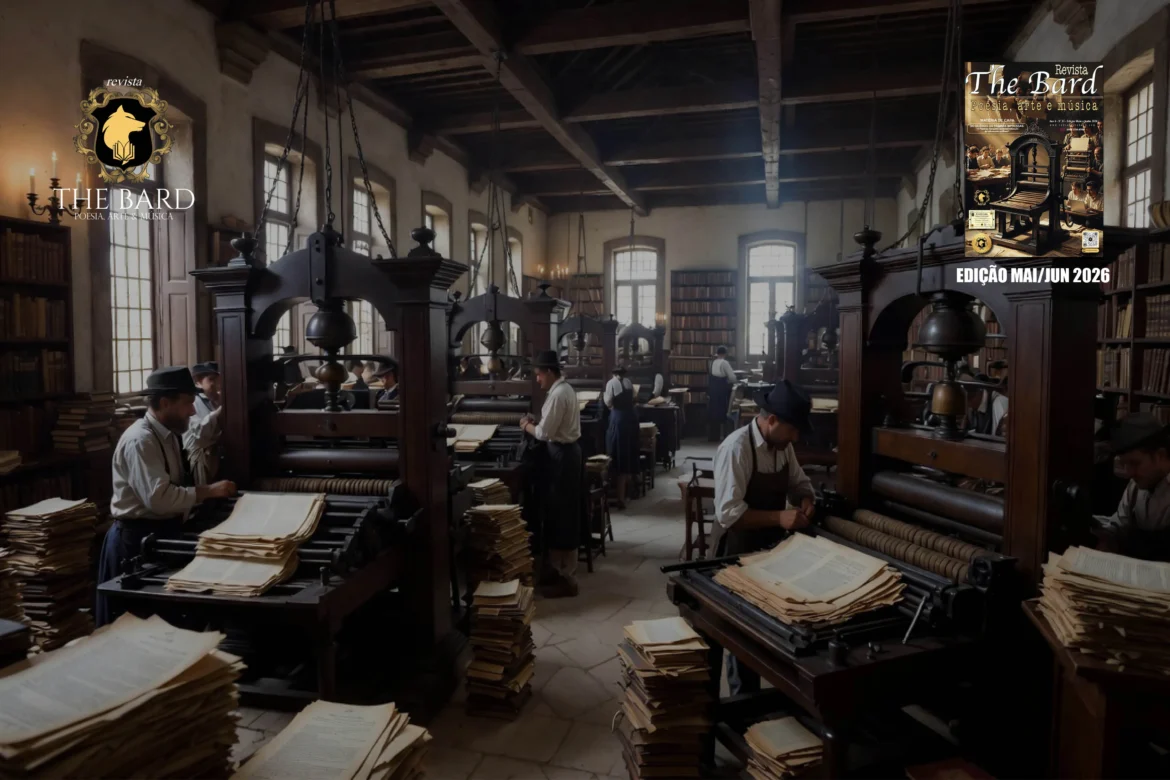
“A tipografia é o ofício que dá forma visível e durável –
e portanto existência independente – à linguagem humana.”
Robert Bringhurst
A junção das letras deu origem a escrita, há cerca de 4000 a.C., permitiu que a humanidade registrasse seus modos de vida, atravessando barreiras do tempo e preservando informações para o futuro. No mundo antigo, especialmente nas civilizações do Oriente Próximo, como o Egito e a Mesopotâmia, a escrita era um instrumento de poder e controle, raramente acessível à população comum (camponeses, artesãos). Na maior parte da antiguidade a escrever era uma habilidade especializada, restrita e dominada majoritariamente por escribas e sacerdote. Dominar a escrita trazia reconhecimento social e isenção de trabalhos braçais, posicionando os escribas como um grupo de elite, embora abaixo da nobreza e dos altos sacerdotes.
As letras viram palavras, que viram frases,
que viram histórias, que tocam os corações.
Autor desconhecido
Surgimento da tipografia
A escrita era feita à mão por escribas, o que tornava os livros raros e caros. Diferente dessa produção manual a tipografia é a arte, técnica e processo de organizar letras, fontes e caracteres para tornar a linguagem escrita legível, clara e visualmente atraente. Práticas de impressão em superfícies macias já existiam na Mesopotâmia (selos) e China (blocos de madeira no século II d.C.), contudo, o surgimento da tipografia moderna é marcado pela invenção da prensa de tipos móveis metálicos por Johannes Gutenberg na Alemanha, por volta de 1450, criando letras e símbolos em relevo esculpidos em metal, capazes de aumentar os números na produção, diminuir o valor em cima, e disseminar a informação. O primeiro livro inteiro publicado pela técnica da imprensa foi a bíblia.
História da tipografia no Brasil
No Brasil, a história da tipografia se mistura às transformações sociais, culturais e tecnológicas que o país passou ao longo dos séculos. Até o início do século XIX, o país, então colônia de Portugal, vivia sob forte controle informativo. A impressão de livros e jornais era proibida por lei, qualquer material gráfico precisava ser produzido em território português. Ainda assim, há registros de tentativas de instalação de oficinas tipográficas, como a do impressor português Antônio Isidoro da Fonseca, em 1747, no Rio de Janeiro. Seu trabalho foi interrompido pelas autoridades da época.
Com a vinda da família real portuguesa ao Brasil em 1808, tudo mudou. Foi fundada a Impressão Régia, primeira tipografia oficial do país, no Rio de Janeiro. Inicialmente restrita aos interesses da Corte para imprimir leis e decretos. A tipografia permitiu o surgimento do primeiro jornal brasileiro, a Gazeta do Rio de Janeiro, iniciando o processo de disseminação de notícias para além dos manuscritos clandestinos.
Nesse sentido, as primeiras iniciativas para a instalação de uma tipografia teve inicio em 1634 (Recife) com o registro de um pequeno folheto (Brasilsche Gelt-Sack) impresso durante a ocupação holandesa. O folheto é um panfleto de caráter político e econômico que questionava o destino do dinheiro dos acionistas da Companhia das Índias Ocidentais (WIC).
Temos em seguida a figura do impressor António Isidoro da Fonseca foi, de fato, o responsável pela primeira oficina tipográfica de que se tem registro no Rio de Janeiro, em 1747. No entanto, sua iniciativa foi curta devido à política de censura da Coroa Portuguesa.
Só em 1808 (Rio de Janeiro – Imprensa Régia): Fundada em 5 de janeiro (embora o decreto seja de maio), tornou-se a primeira tipografia oficial, essencial para imprimir leis e documentos da corte. Surge o Primeiro Jornal: A Gazeta do Rio de Janeiro que começou a circular em 1808, marcando o início da imprensa periódica oficial. Após a Imprensa Régia, outras oficinas surgiram no século XIX, como a tipografia de Georges Leuzinger e a de Eduardo e Henrique Laemmert. A partir de 1822, com a Independência do Brasil, surgiram dezenas de novas oficinas gráficas e jornais. A técnica tipográfica começou a se espalhar por cidades como Salvador, Recife, São Paulo e Porto Alegre.
Desde a chegada da Impressão Régia em 1808, que marcou o início da produção tipográfica por aqui, até os avanços modernos que vieram impulsionados pelo design digital, a tipografia se consolidou com uma ferramenta essencial de comunicação e expressão cultural, transformando ideias em páginas que compõem a memória impressa do país.
Esse crescimento foi impulsionado também pela demanda de livros, folhetos religiosos, panfletos políticos e, principalmente, jornais. A tipografia brasileira começava a criar sua própria identidade, mesclando influências europeias com as demandas e contextos locais.
O século XX foi marcado por grandes transformações tecnológicas. A chegada das máquinas de linotipo, da impressão offset e do fotolito trouxeram mais agilidade, precisão e qualidade ao mercado gráfico. Editoras, jornais e gráficas passaram a investir em design editorial, e com isso, a tipografia passou a ter um papel de destaque no visual das publicações.
Nessa época, surgem no Brasil movimentos de valorização do design gráfico como linguagem e identidade cultural, algo que influenciou profundamente o uso criativo das fontes tipográficas, a escolha de estilos e a construção de marcas editoriais.
A partir dos anos 1990, com a popularização dos computadores e dos softwares gráficos (como Adobe InDesign, Illustrator e CorelDRAW), a tipografia digital ganhou força. Agora, qualquer designer podia criar, modificar e usar fontes em seus projetos de forma prática e acessível.
IMAGEM GERADA POR IA “usando GROK.AI, sob a direção de J.B Wolf, Criada em 21/04/2026″
Além disso, surgiram fontes tipográficas criadas por brasileiros, com forte influência da nossa cultura, linguagem e estética visual. A tipografia se tornou mais democrática, criativa e plural, conectando-se com marcas, publicações e expressões artísticas contemporâneas.
A importância da tipografia nos dias de hoje
Na era contemporânea, a tipografia desempenha um papel técnico crucial para garantir que a informação chegue a todos os cidadãos, independentemente de suas limitações físicas ou cognitivas.
O uso de fontes adaptadas para pessoas com deficiência visual ou dislexia é fundamental para a inclusão social. Seguido do lançamento da norma ABNT NBR 17225 estabelece padrões de acessibilidade digital para sites no Brasil, onde a escolha tipográfica adequada é um dos critérios para garantir que o conteúdo web seja plenamente acessível. Também o uso de tipografia e design de informação no campo jurídico (como guias de simplificação do Tribunal do Rio de Janeiro) ajuda a humanizar e traduzir termos complexos para a população em geral.
Em um mundo visual, o texto precisa ser mais do que lido, ele deve ser sentido. A tipografia certa melhora a leitura, comunica emoção, gera impacto e traduz a essência de uma marca.
Seja em livros, revistas, catálogos, embalagens ou identidades visuais, a tipografia continua sendo essencial para quem quer se destacar e criar conexão com seu público.